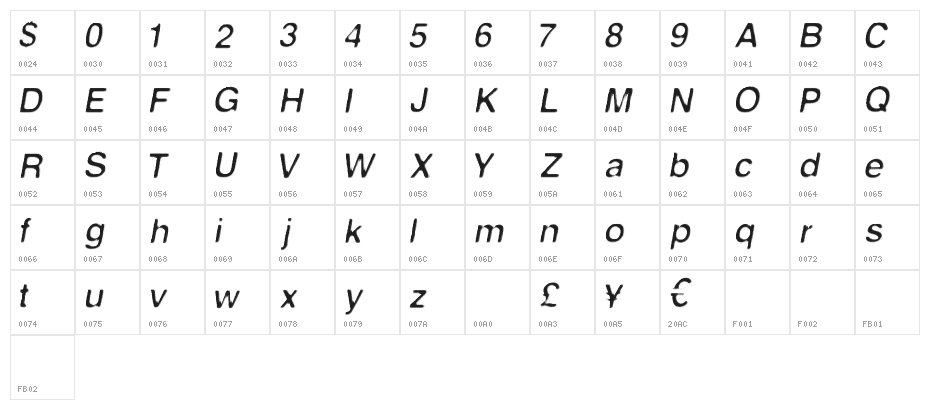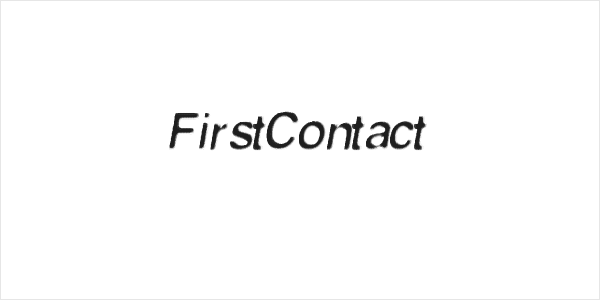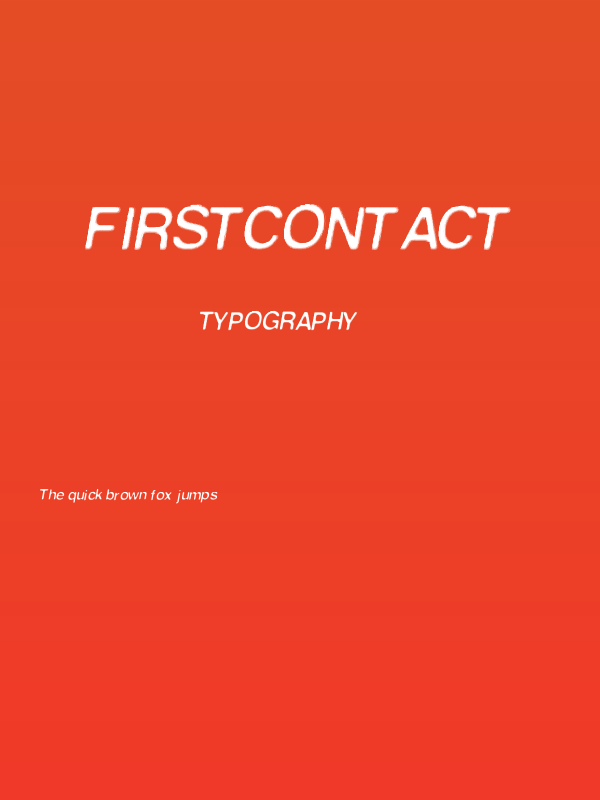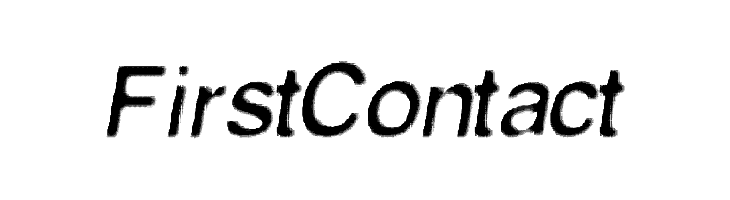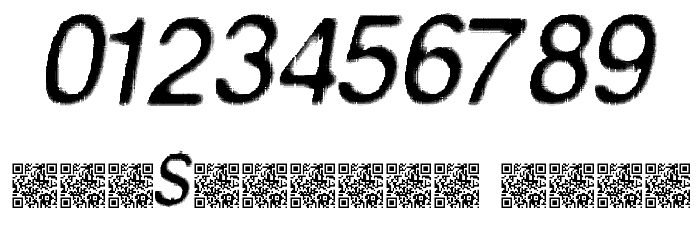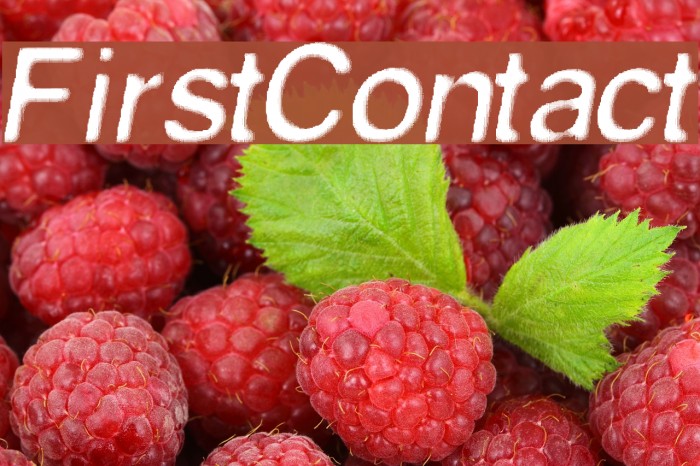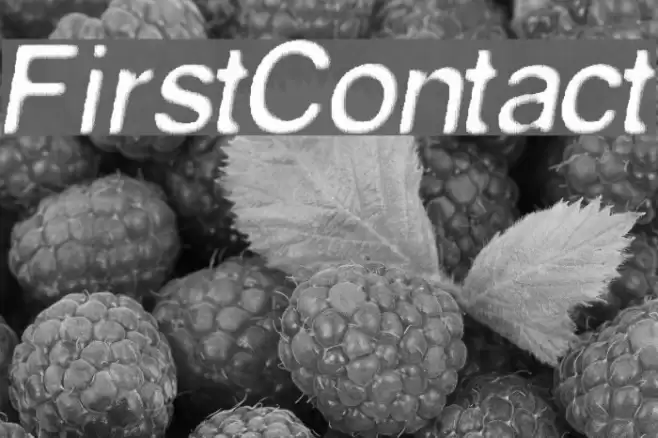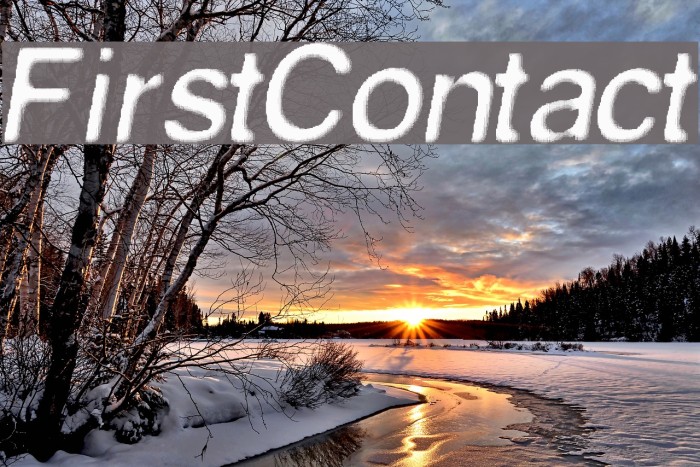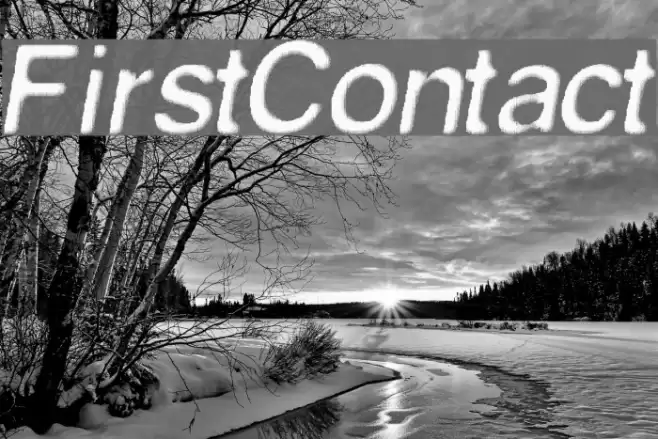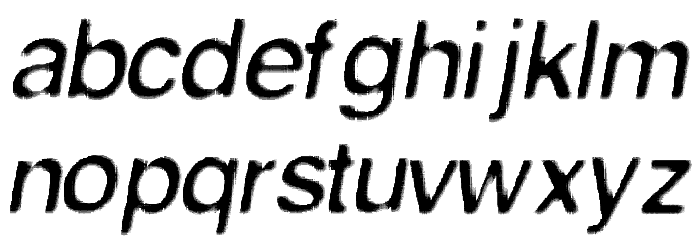
FirstContact Font
✎ Distorted Eroded
| Anwendungsfall | Headlines, Logos, Digital Media |
| Vorgeschlagene Projekte | Ideal for branding, advertising, and digital media projects where a modern and dynamic look is desired. |